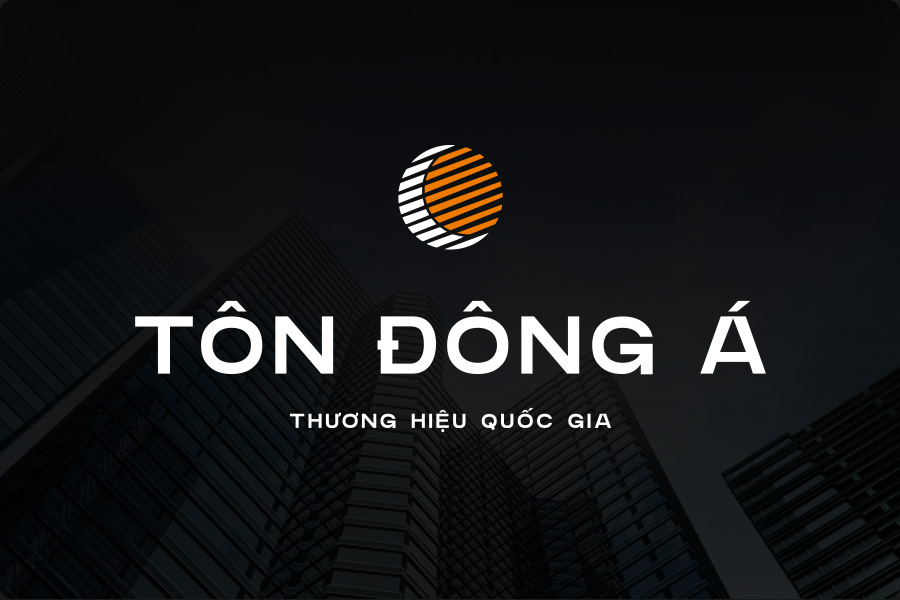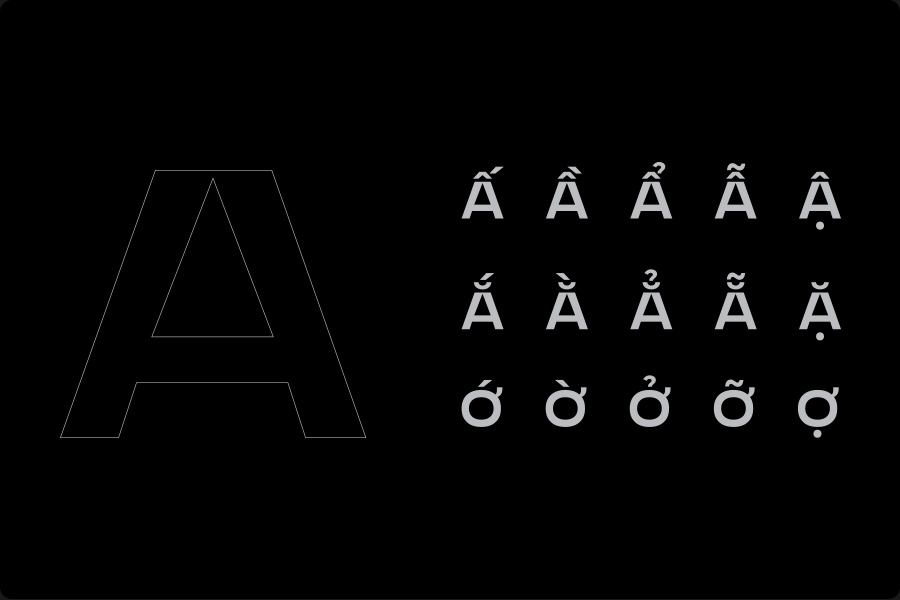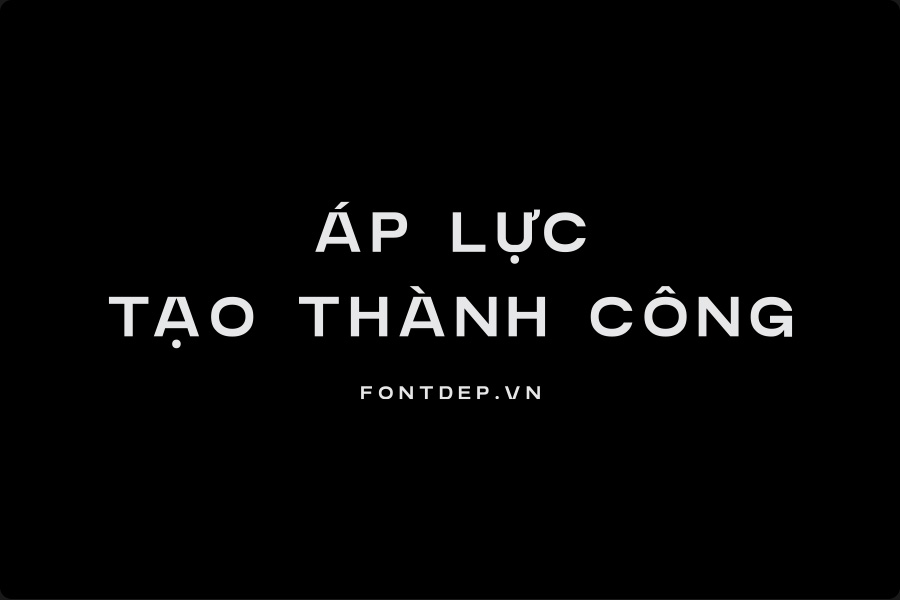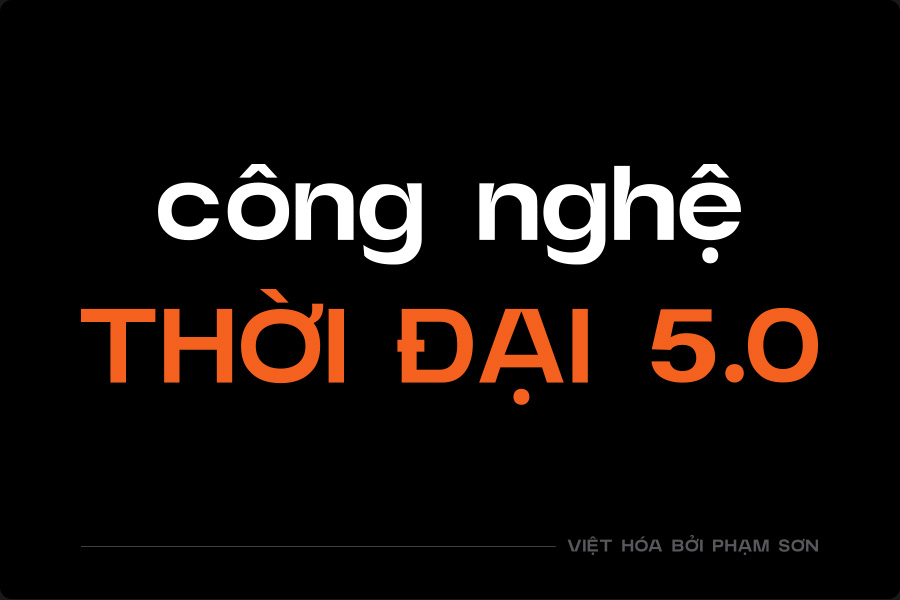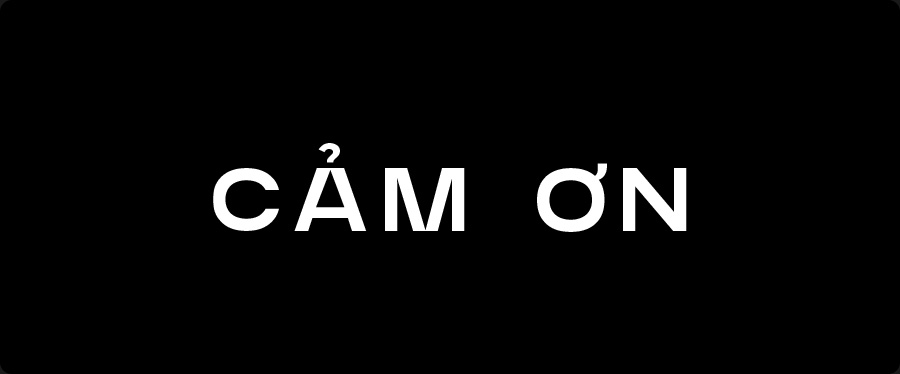
Font chữ Sans-serif không chân hiện đại, tối giản TH Artega
Nếu bạn đang tìm một font chữ hiện đại, gọn gàng và dễ sử dụng cho các thiết kế như tiêu đề, poster, giao diện web hay bài thuyết trình, thì TH Artega là một gợi ý rất đáng để thử. Đây là một kiểu chữ sans-serif được thiết kế theo phong cách hình học, với các đường nét tròn đều và hài hòa – mang lại cảm giác vừa chuyên nghiệp vừa thân thiện với người đọc.
Thiết kế tối giản nhưng hiệu quả cao
Font TH Artega được phát triển bởi Yukita Creative, một nhóm thiết kế chuyên tạo ra những kiểu chữ mang hơi hướng hiện đại và dễ ứng dụng. Với kiểu dáng không chân, các nét tròn mềm mại và khoảng cách giữa các chữ được cân chỉnh hợp lý, TH Artega giúp văn bản hiển thị rõ ràng và dễ đọc trên mọi nền tảng, từ máy tính, điện thoại đến bảng in poster hoặc slide trình chiếu.
Chữ cái trong TH Artega được tạo dựng theo phong cách hình học (geometric), nghĩa là các đường nét được xây dựng dựa trên các hình tròn và đường thẳng cơ bản. Nhờ vậy, font trông rất cân đối, phù hợp với những thiết kế yêu cầu sự tối giản và hiện đại, chẳng hạn như các dự án công nghệ, khởi nghiệp, thương hiệu sáng tạo hay nội dung giáo dục.
Một điểm đặc biệt quan trọng: font TH Artega đã được Việt hóa hoàn chỉnh bởi Phạm Sơn, Admin S99.vn và Fontdep.vn.
Bản Việt hóa này đảm bảo đầy đủ các dấu tiếng Việt, đặt dấu chính xác, không bị lỗi chồng hoặc lệch glyph như nhiều bản font gốc nước ngoài. Điều này giúp người dùng Việt có thể sử dụng TH Artega một cách chuyên nghiệp và linh hoạt trong mọi thiết kế, từ in ấn đến kỹ thuật số.
Phiên bản Việt hóa được đánh giá cao nhờ tính đồng bộ, giữ trọn vẹn phong cách nguyên bản của Artega nhưng được tối ưu hóa hoàn toàn cho tiếng Việt.
TH Artega là một font chữ sans-serif hình học hiện đại, dễ đọc và dễ phối hợp trong nhiều loại thiết kế. Nhờ vào thiết kế tối giản, đường nét rõ ràng và độ tương thích cao, TH Artega xứng đáng có mặt trong bộ sưu tập font của bạn – đặc biệt nếu bạn đang hướng đến các thiết kế sạch sẽ, chuyên nghiệp và tiết kiệm chi phí.